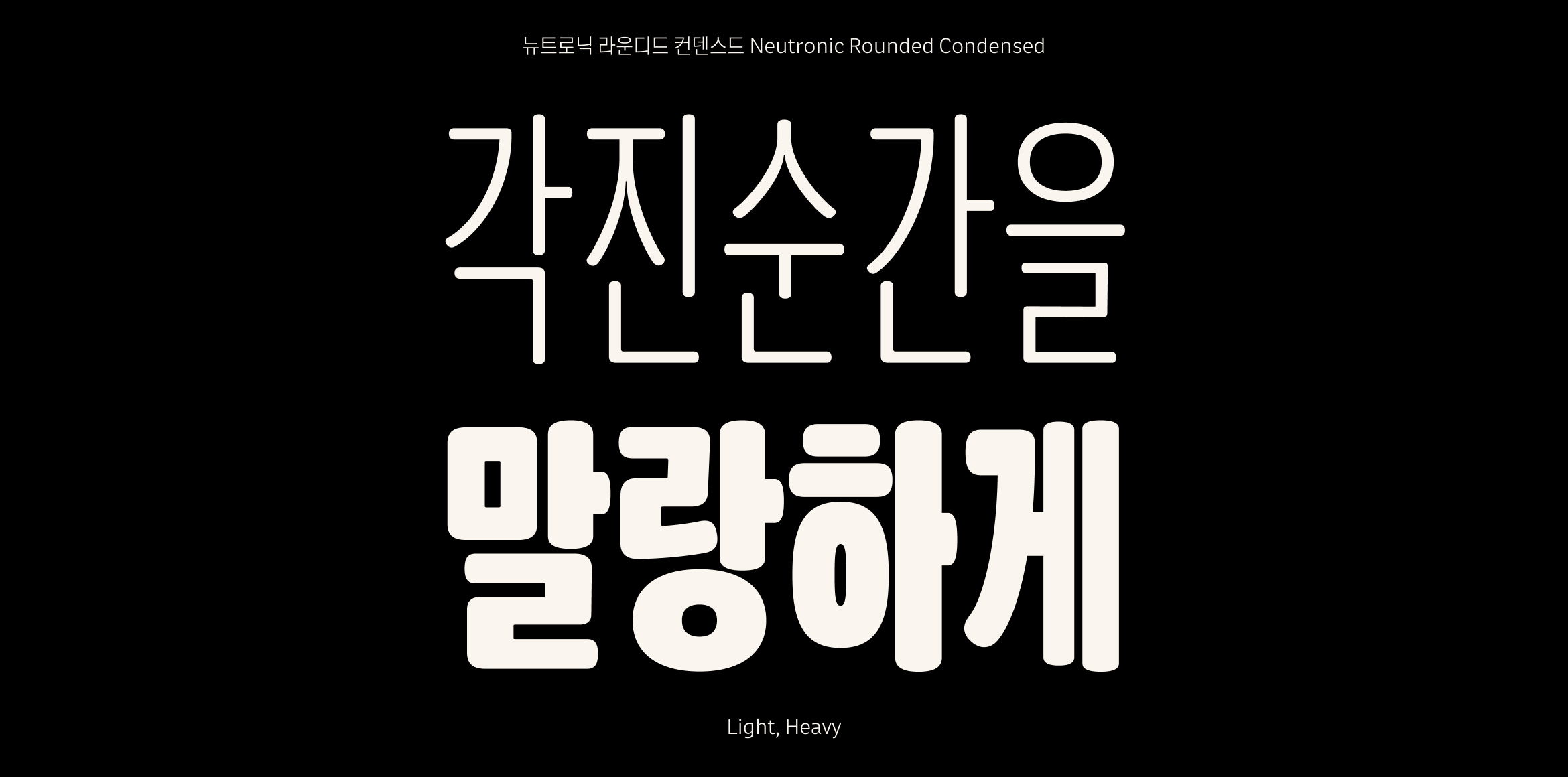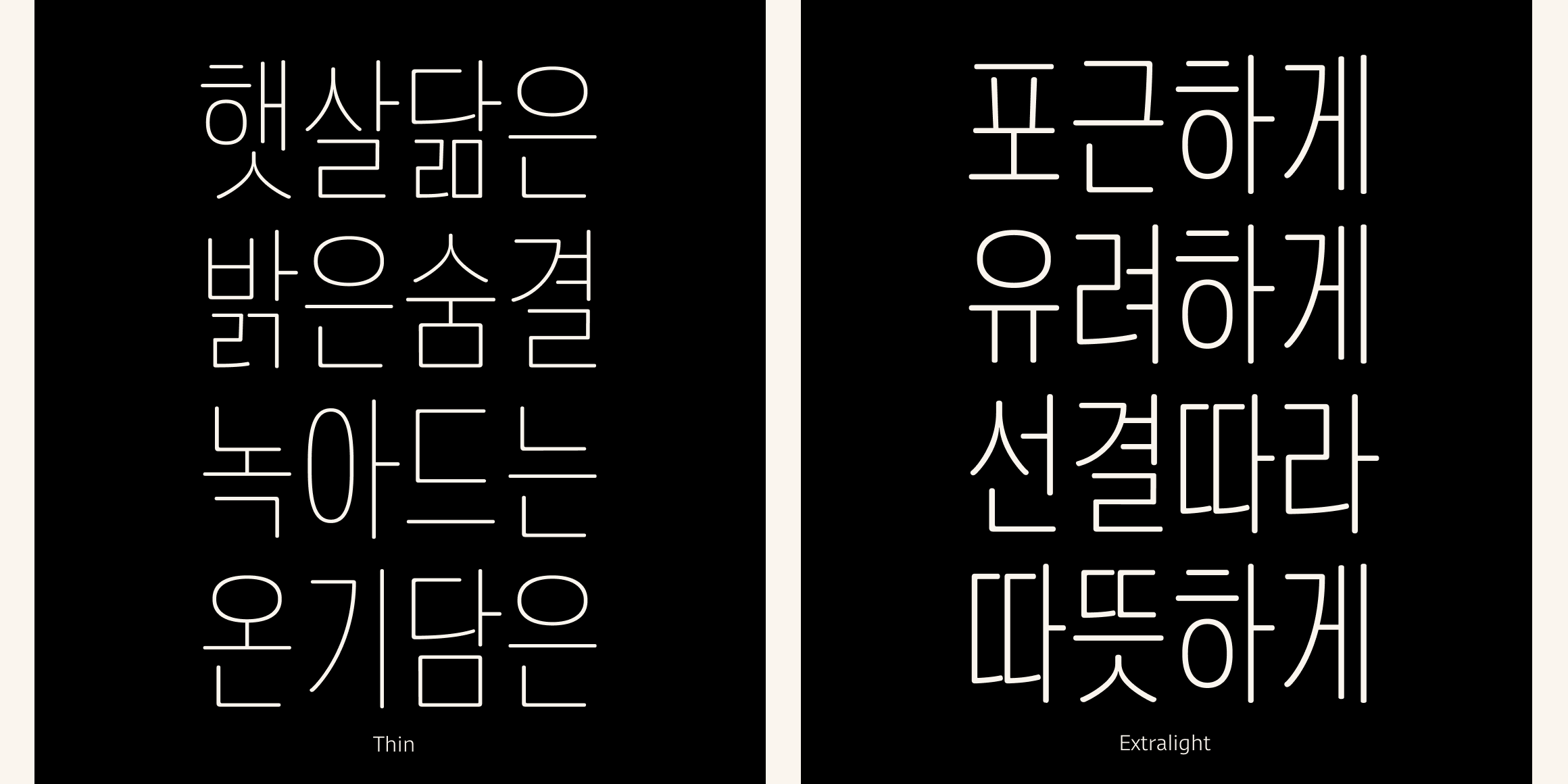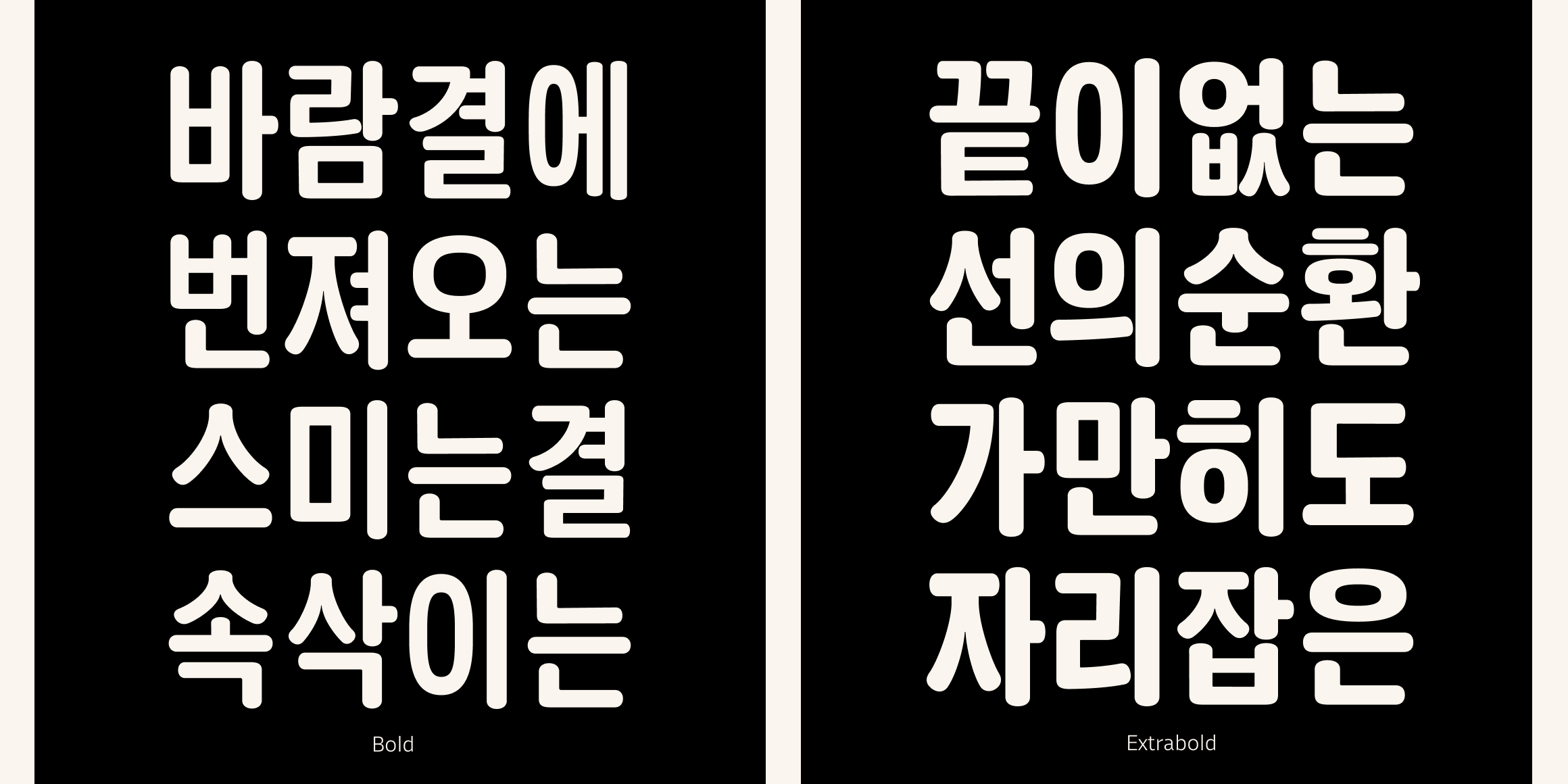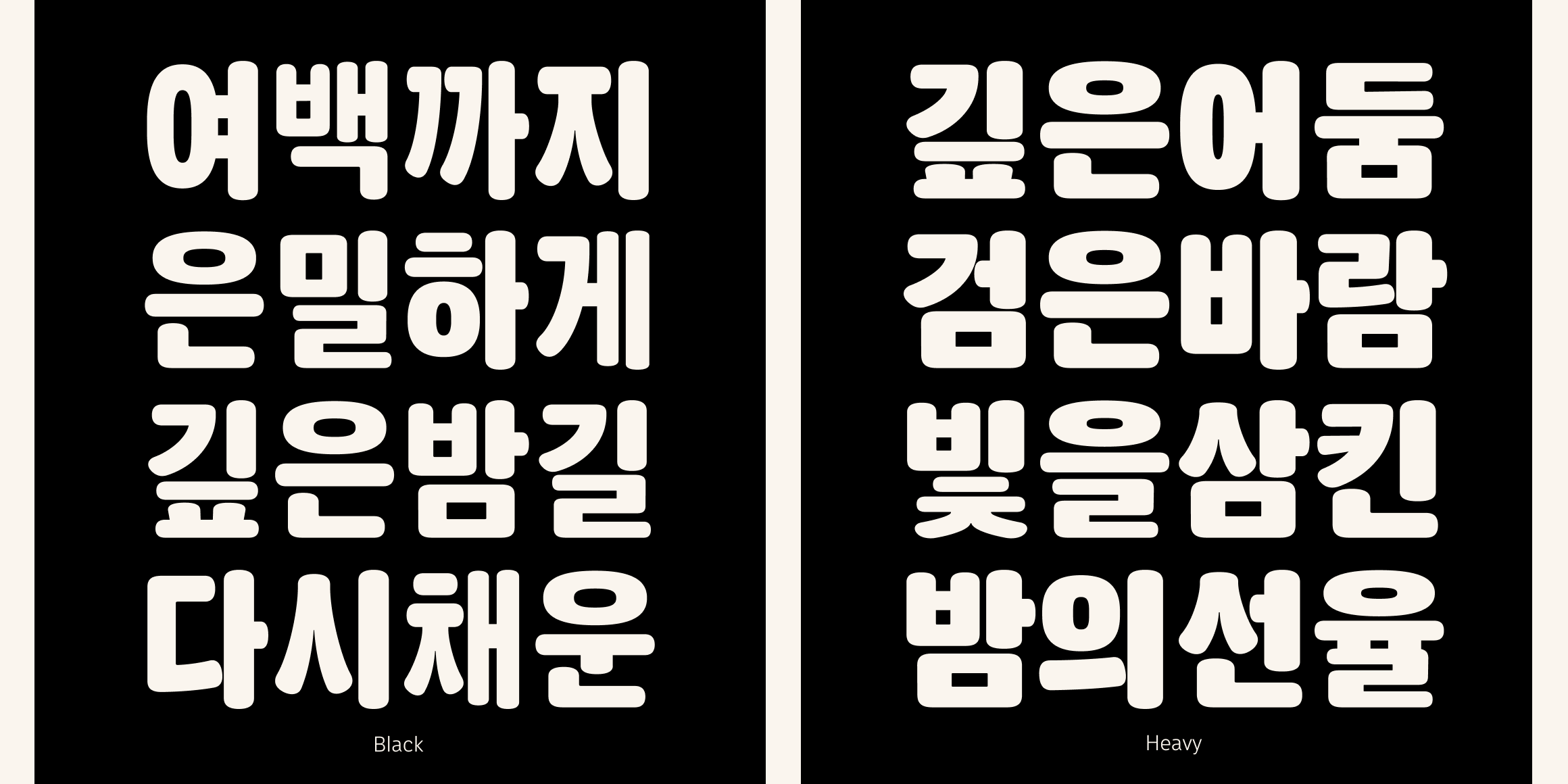
뉴트로닉한글 컨덴스드
분류 Sans,디스플레이,민부리
뉴트로닉 한글 컨덴스드는 뉴트로닉 한글의 컴프레스드와 내로우의 중간 폭 입니다. 기존의 경직되고 딱딱한 표정의 고딕(민부리 스타일)이 아닌 자연스럽고 신선하며 깔끔한 컨셉으로 그렸습니다. 글줄 상단으로 무게 중심을 두어 짧은 문장 뿐만 아니라 긴 글에도 글줄이 정돈되어 보입니다.
군더더기 없는 디자인을 추구하며ㅅ, ㅈ, ㅊ 등은 대칭의 형태를 택하였고 글자의 인상에 중요한 곡선을 유기적인 형태로 자연스럽게 표현했습니다.
특히 속공간의 형태와 비례를 세심하게 디자인 했습니다. 초성과 중성을 사이의 곁줄기를 연결하지 않고 간격을 두어 공기가 흐르는 속공간을 연출했습니다. 이러한 요소들은 긴 텍스트에서도 고른 컬러와 질감으로 나타납니다.
가장 굵은 Heavy는 형태의 특징이 더 두드러지고 부각되어 시선을 잡고자 하는 책의 제목이나 포스터, 영상의 썸네일, 간판 등에 사용하면 좋습니다.
가장 가는 Thin은 이미지 위에 대비해서 사용하거나 크게 사용하여 깔끔한 강조를 하기에 좋습니다.